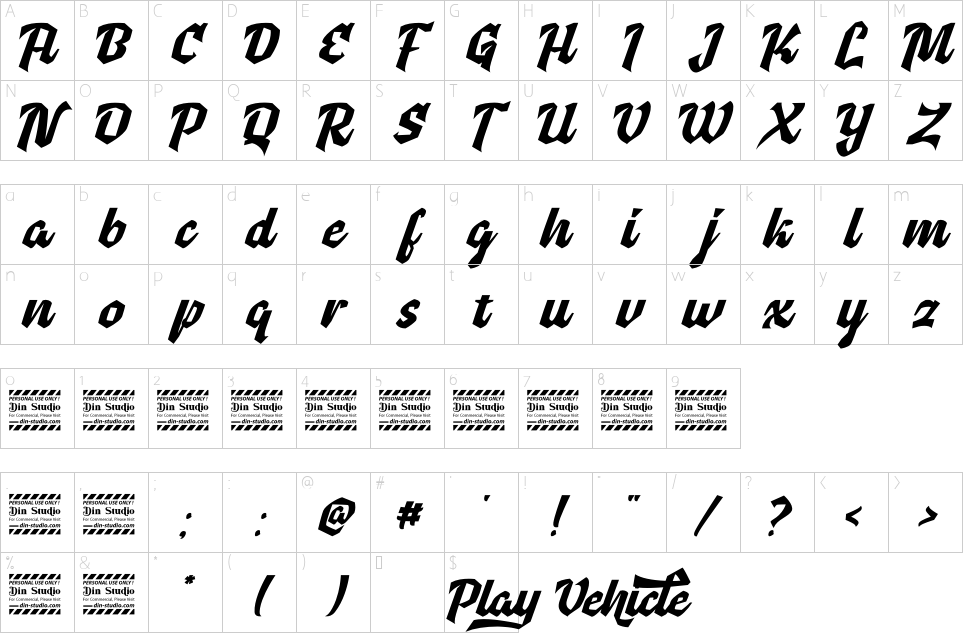
Play Vehicle Font – Download Grátis
A Play Vehicle é uma fonte criada pelo Din Studio que se destaca por sua característica vibrante e dinâmica. Inspirada nos veículos modernos que enchem as ruas do Brasil, esta fonte oferece um toque de energia urbana para qualquer projeto gráfico ou design digital. Ela foi projetada especificamente para proporcionar uma mistura única entre a eficácia funcional e o estilo vibrante dos automóveis atuais, fazendo dela uma excelente escolha para designers buscando dar vida a seus trabalhos digitais. Se você está procurando por uma fonte que ressoe com as marcas de nossos carros no Brasil ou até mesmo se identifique com a velocidade e eficiência das cidades brasileiras, Play Vehicle pode ser a solução perfeita para seu projeto.